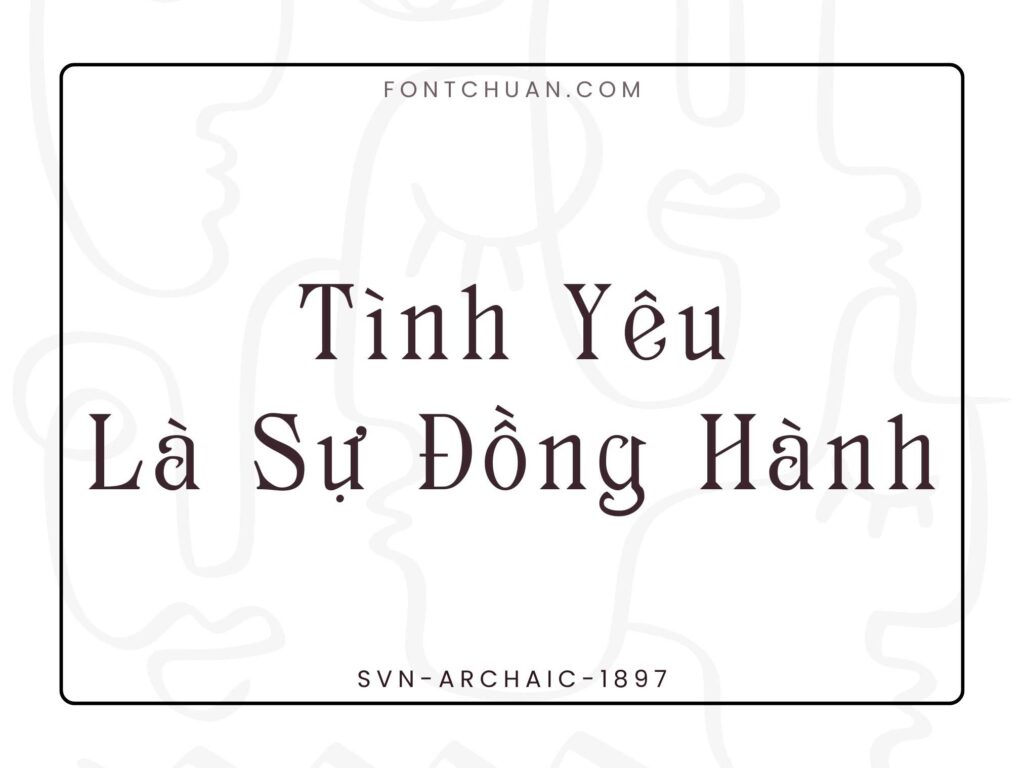
Font SVN Archaic 1897 Việt Hóa
Archaic 1897 là một font chữ mang phong cách cổ điển, được thiết kế bởi Pilaster Davy và phát hành lần đầu vào năm 2015. Font này được lấy cảm hứng từ các kiểu chữ của American Type Founders (ATF) cuối thế kỷ 19, mang đến sự hoài cổ và độc đáo cho các thiết kế. Archaic 1897 được cung cấp miễn phí cho mục đích sử dụng cá nhân và có sẵn dưới định dạng TrueType (.ttf) với một kiểu chữ duy nhất. Font đã được Việt hóa để hỗ trợ tiếng Việt bởi Styleno.1 Fonts, đồng thời hỗ trợ nhiều ngôn ngữ khác, giúp mở rộng phạm vi sử dụng trên toàn cầu. Font này được thành viên của Font Chuẩn sưu tầm và chia sẻ, đáp ứng nhu cầu của bạn đọc và ứng dụng thực tế vào các dự án thiết kế.
Đặc điểm thiết kế của Archaic 1897 bao gồm các đường nét cổ điển, tạo cảm giác hoài cổ và độc đáo. Font này phù hợp cho các ứng dụng như thiết kế poster, tiêu đề, ấn phẩm quảng cáo và các dự án sáng tạo khác. Các ngành nghề phù hợp bao gồm quảng cáo, nghệ thuật và thiết kế sáng tạo.